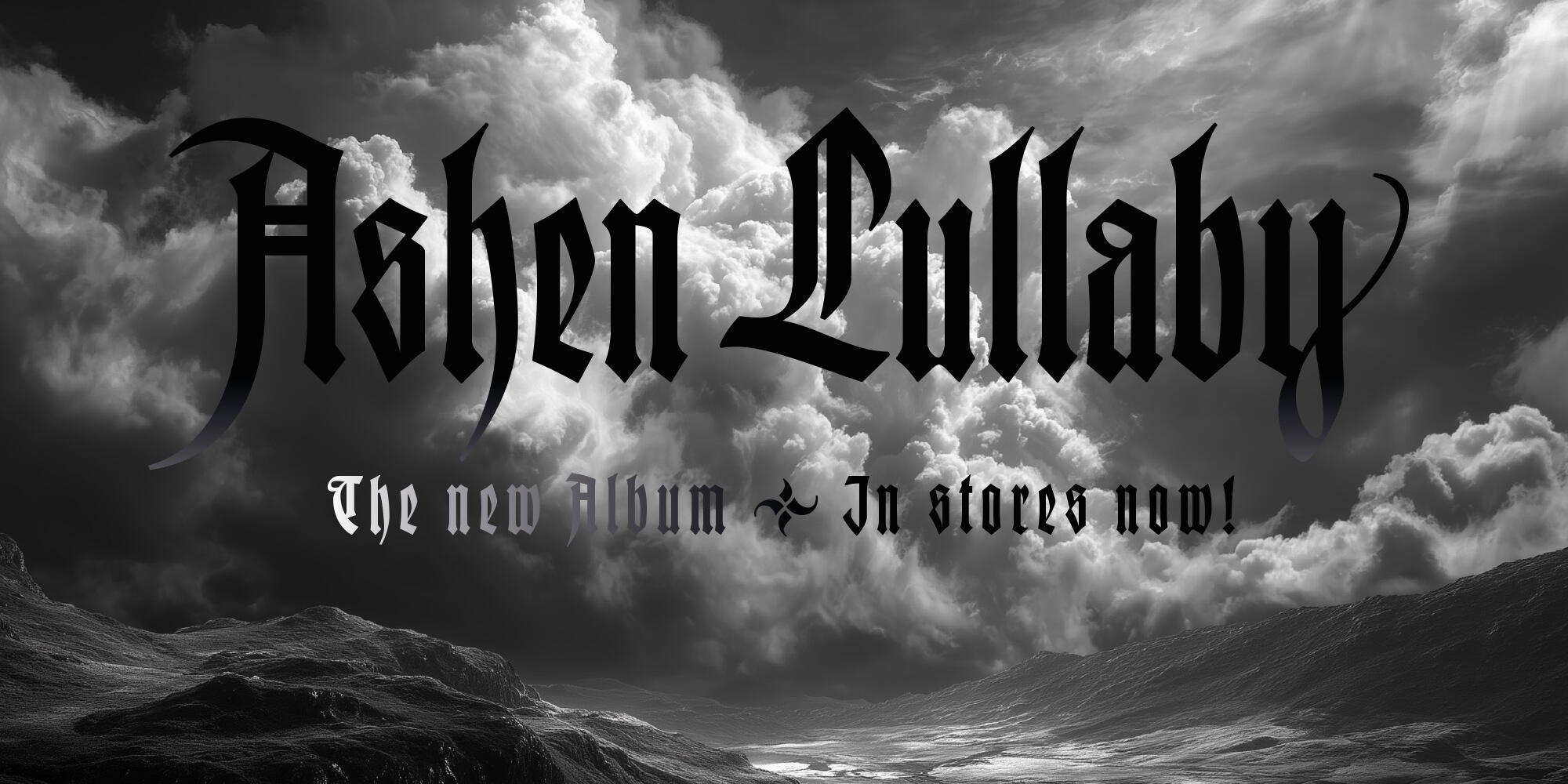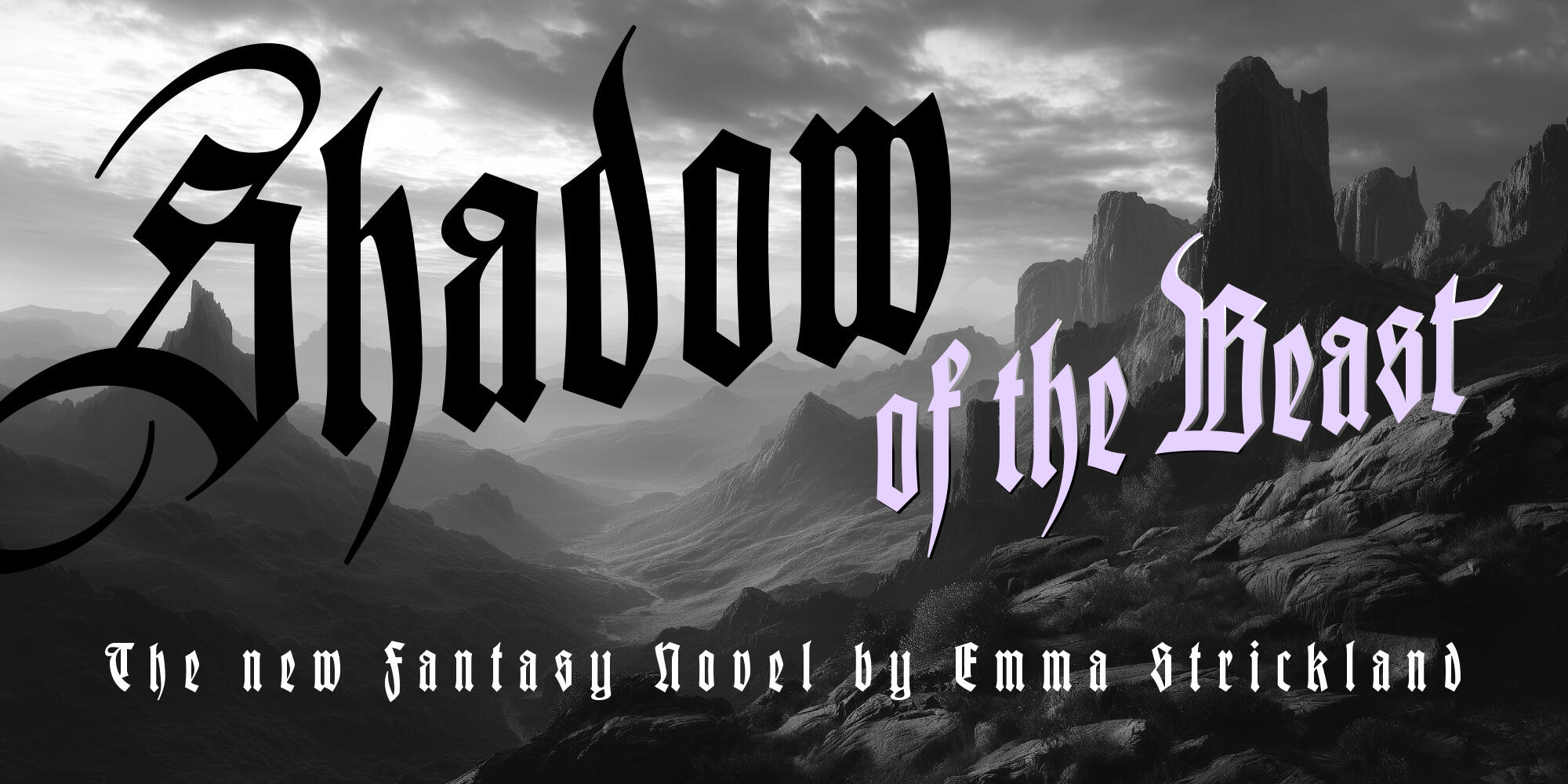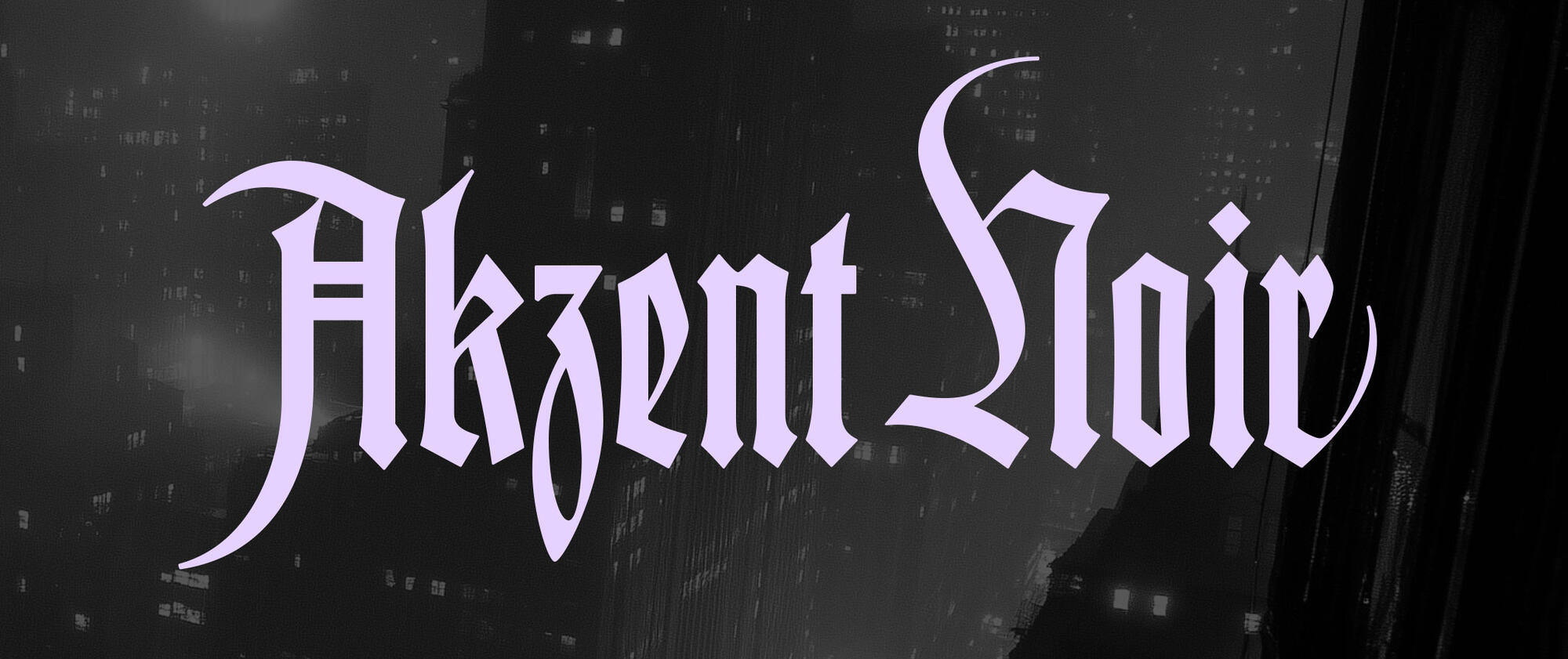
Die Akzent Noir ist eine Digitalisierung der schmalen Deutschen Schrift (1913) von Rudolf Koch einschließlich der Original-Schwungbuchstaben und Ligaturen. Der Zeichensatz umfasst eine westeuropäische Belegung nach MacRoman/Win 1252.